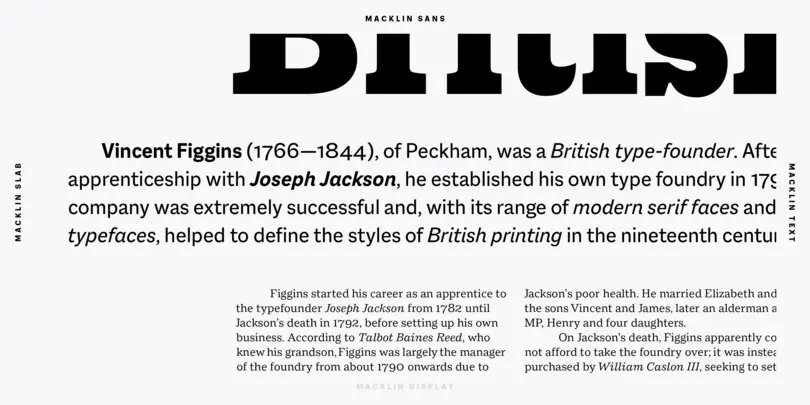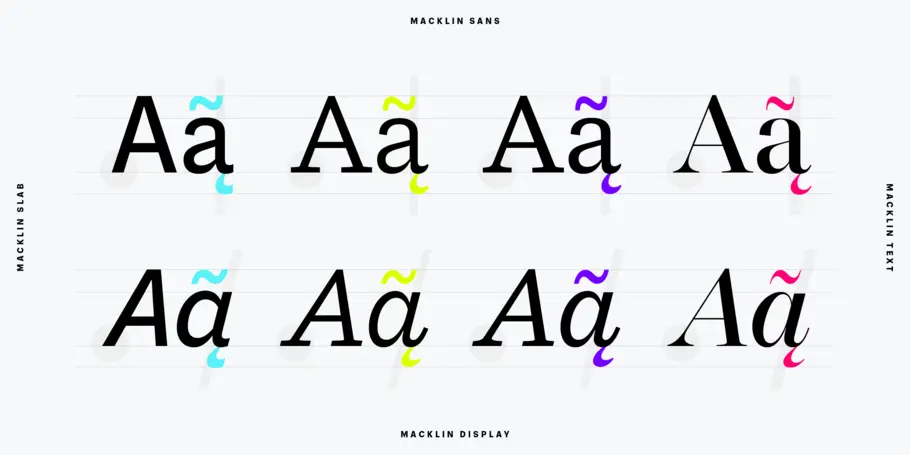
Qu’est-ce qu’une superfamille de polices et pourquoi en avons-nous besoin ?
Je pense que si une police dispose d’une large variété de graisses et de chasses, c’est une grande famille. Ce qui la rend "super", c’est sa capacité à changer de personnalité ou de voix tout en restant en harmonie.
Terrance Weinzierl.
La typographie a beaucoup évolué depuis le temps des caractères d’imprimerie. À l’époque, posséder une poignée d’entre eux, c’était avoir une grande variété de choix. Aujourd’hui, les marques et les designers ont besoin de toute une panoplie de polices couvrant différents styles, tailles et alphabets. Cela engendre un besoin accru de superfamilles — vastes collections de caractères pouvant répondre à une multitude de besoins, sans compromettre la cohérence. Mais qu’entend-on exactement par superfamille ?
« Pour moi, une superfamille se définit par la déclinaison de plus d’un style, qui, admettons,  comprend un sans et un avec serif, mais ce n’est pas gravé dans le marbre », explique Terrance Weinzierl, designer typographique senior chez Monotype. « Je pense que si une police dispose d’une large variété de graisses et de chasses, c’est une grande famille. Ce qui la rend «super», c’est sa capacité à changer de personnalité ou de voix tout en restant en harmonie et en conservant une partie du même système, peut-être des métriques verticales et des couleurs de graisses visuelles. »
On peut comparer cela aux couleurs analogues. Une grande famille de caractères propose des teintes de bleu clair à bleu foncé, là où une superfamille offre le spectre entier de cette couleur — du bleu-vert jusqu’aux nuances jaunes et violettes. En s’appuyant sur la même architecture de base des lettres, les superfamilles permettent aux designers d’associer différents styles sans créer de combinaisons maladroites.
La superfamille Macklin de Malou Verlomme en est un excellent exemple, car elle réunit plusieurs styles de lettres dans une seule famille qui inclut une sans, une slab, des versions Text et Display. Parce qu’ils partagent un squelette commun, chacun de ces styles peut fonctionner en collaboration avec les autres.
Une boîte à outils complète pour les marques.
C’est précisément cette harmonie interne qui donne aux superfamilles toute leur valeur pour les marques. Elles permettent aux entreprises d’investir dans une police de caractères unique pouvant répondre à de multiples besoins créatifs, tout en laissant aux designers une marge de manœuvre pour l’avenir.
Les superfamilles peuvent être extrêmement précieuses pour l’éditorial, où les caractères sans et avec serif doivent être utilisés ensemble plutôt qu’en opposition, ou pour les entreprises qui ont besoin d’une police à espacement unique pour les environnements de codage. Les marques qui lancent de nouveaux produits, élargissent leur champ d’action ou encore s’établissent sur de nouvelles plateformes, ont souvent besoin d’une nouvelle approche design. Une superfamille leur permet d’y arriver tout en conservant la cohérence de leur marque.
This image shows how three styles of Macklin—Slab for the headline, Sans for the subhead, and Text for the body—can be used to lay out a single editorial piece. Superfamilies like this give you the range to distinguish different blocks of text while maintaining a strong visual throughline.
« Vous pouvez utiliser une superfamille dans votre charte graphique pour distinguer une nouvelle gamme de produits, attitude ou tonalité, qui restera toutefois similaire et reconnaissable », explique Weinzierl.
« Imaginez qu’une entreprise de meubles lance une gamme pour les enfants », ajoute Weinzierl. « La marque principale utilise le sans, et la gamme pour enfants adopte la version arrondie de cette police. Elle est instantanément plus conviviale et plus sûre, tout en conservant l’identité de la marque. Cette approche utilise la nuance entre les polices plutôt que le fort contraste. »
Vous pouvez utiliser une superfamille dans votre charte graphique pour distinguer une nouvelle gamme de produits, attitude ou tonalité, qui restera toutefois similaire et reconnaissable.
Terrance Weinzierl.
Avec un tel éventail de choix, les designers qui abordent les superfamilles ne savent pas toujours par quoi démarrer. Pour les designers qui se sentent dépassés par ce foisonnement, Weinzierl recommande de commencer petit. Investir dans quelques graisses permet aux utilisateurs de se familiariser avec la police et de s’y habituer. Cela donne également aux designers le temps de comprendre comment ils pourront la compléter et la nuancer. Investir dans une palette limitée, qui pourra être enrichie ultérieurement, est également utile pour de jeunes entreprises ou designers travaillant sur les prémices d’un branding, en réduisant une partie du coût initial des licences.
« Les superfamilles sont utiles pour les premières étapes d’un plus vaste projet. Cela permet de spéculer sur les besoins futurs de la marque », explique Weinzierl. « Admettons que vous travaillez sur une nouvelle marque et que vous n’êtes pas encore certain de vos livrables, mais que vous devez tout de même choisir quelque chose pour votre prototype. Opter pour une superfamille à ce stade, c’est miser sur une base qui vous offre la possibilité de vous réorienter vers des tons plus légers ou plus lourds par la suite. Cela peut également assurer la longévité d’une marque qui en est à son lancement. »
« Alors que nos ordinateurs, ainsi que tout le design et le code qui les entourent, deviennent de plus en plus complexes, la question se pose de savoir comment nous pouvons réajuster l’ambiance au sein d’un design », explique Weinzierl. « Pourquoi cette police ne pourrait-elle pas être arrondie dans ces circonstances ? Pourquoi ne pourrait-il pas y avoir un empattement sous celle-ci ? Les limites se transformeront en opportunités, parce que tout le reste est déjà très ouvert. »